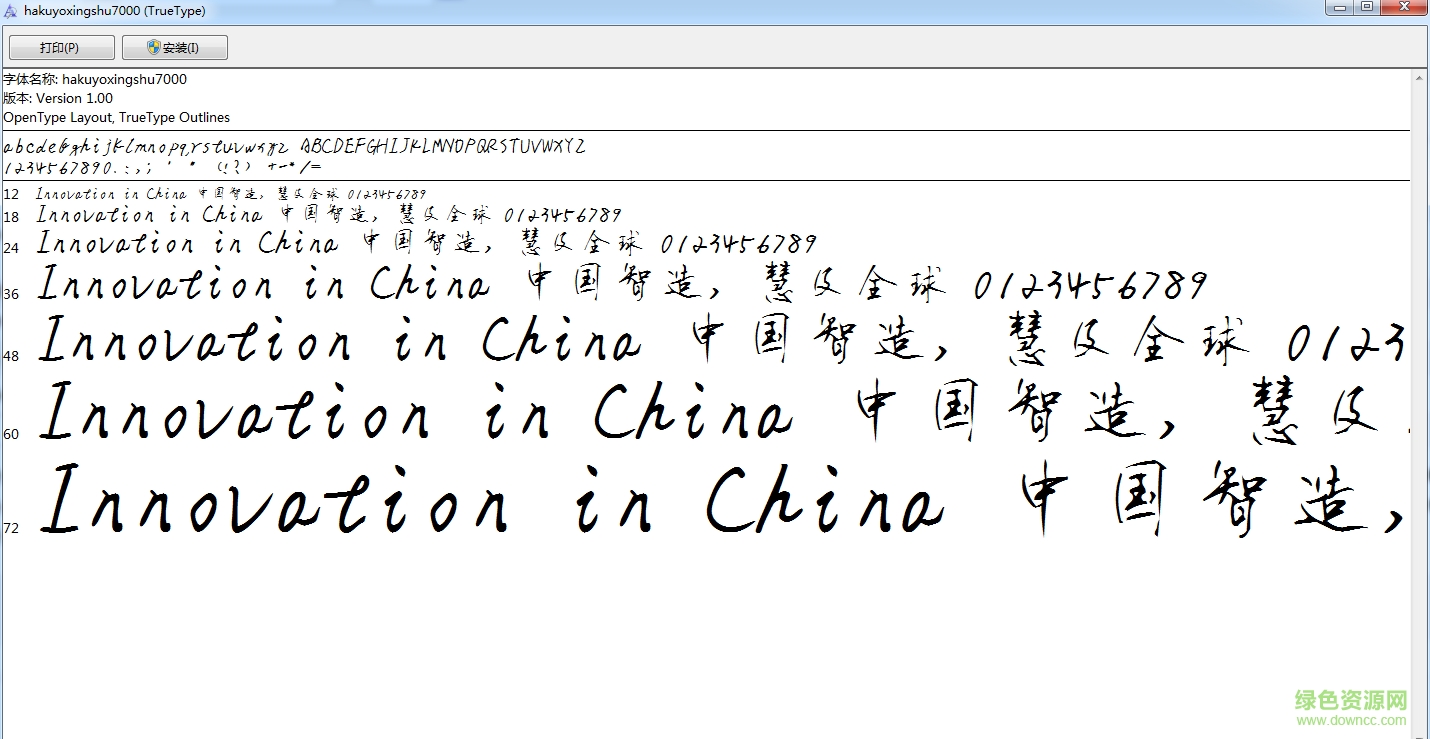
hakuyoxingshu7000 普通体
hakuyoxingshu7000又称博洋行书7000字体,是一款洒脱漂亮的行书字体,线若游丝,撇捺舒展,笔画飞扬,需要的朋友快来绿色资源网下载收藏吧1
行书字体介绍
行书是介于楷、草间的一种书体。写得比较放纵流动,近于草书的称行草;写得比较端正平稳,近于楷书的称行楷。
hakuyoxingshu7000普通字体